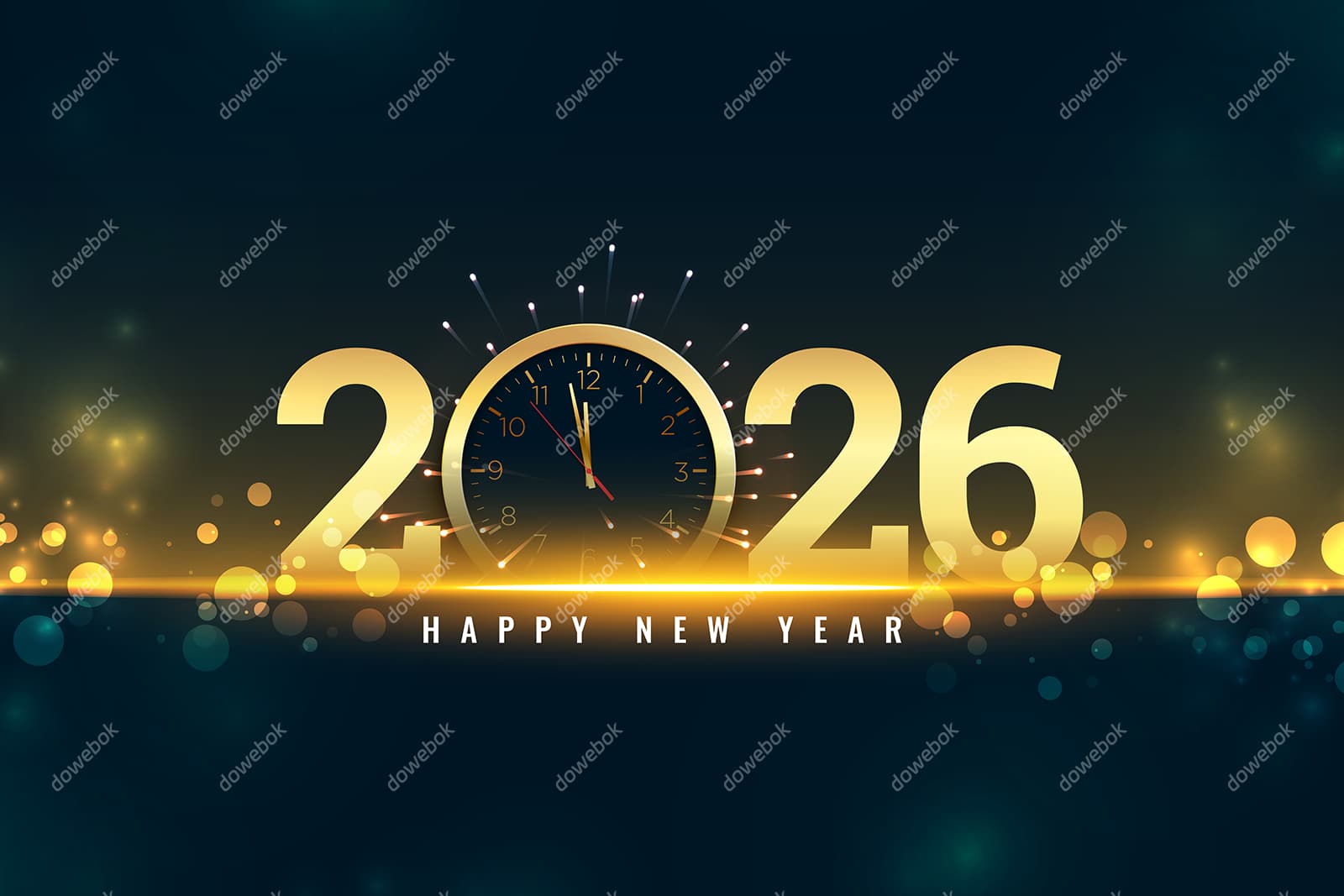
这是一款时钟和金色数字设计 2026 新年快乐矢量素材,深暗背景晕染着金蓝光斑,营造出倒计时的氛围感。金色 “2026” 字体间嵌入时钟元素,指针指向跨年时刻,周围迸射的线条似倒计时的火花。下方衬着简约黑体 “Happy New Year”,整体以时光意象 + 暖金光泽,既显跨年的仪式感,又透出辞旧迎新的期待与热烈。